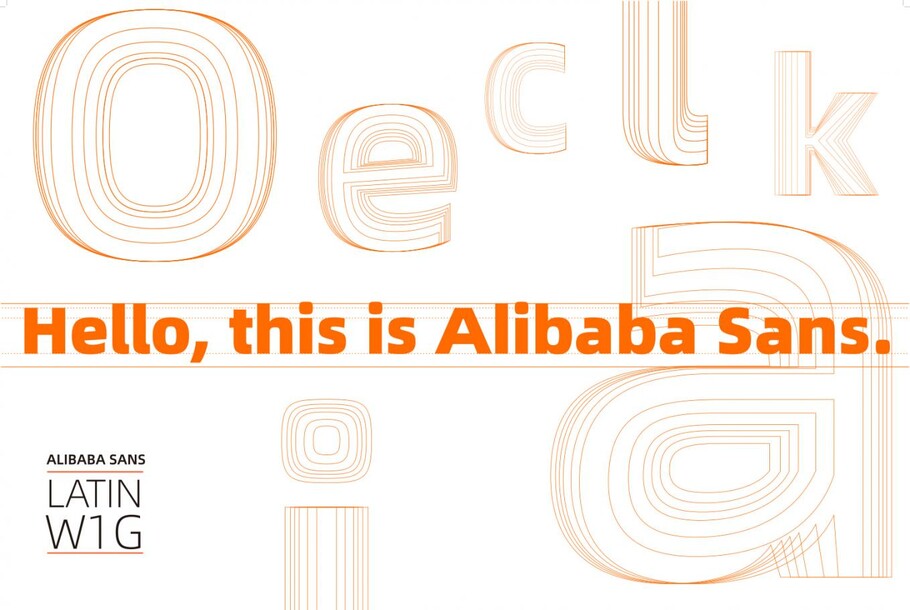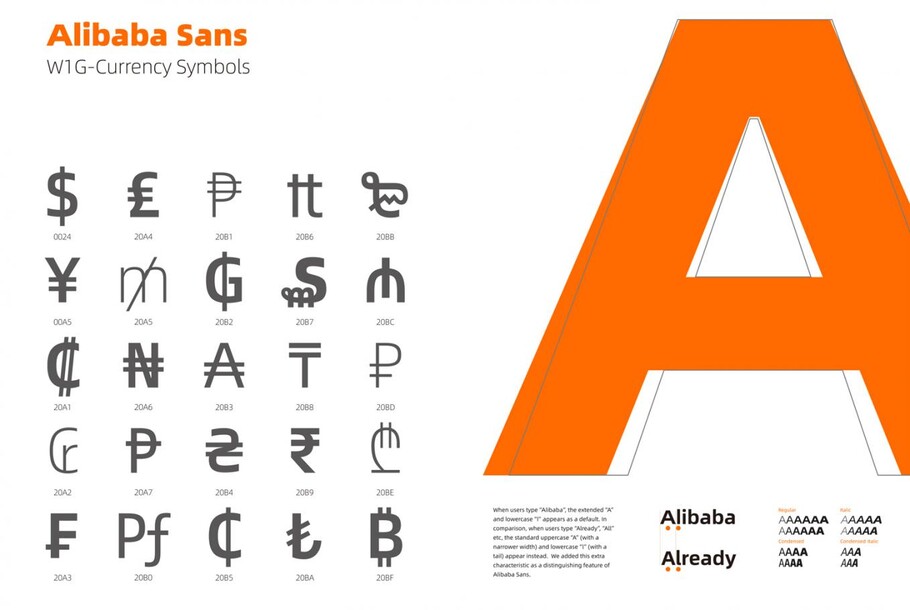
A nova fonte do Alibaba Group traz beleza e simplicidade ao ecossistema da empresa.
“ A Monotype entendeu nossos desafios únicos e entregou uma fonte que elevará nossas iniciativas de branding. ”
Alibaba Sans
Essa família de fontes personalizada, Alibaba Sans, ajudará parceiros e clientes a criar designs que estejam alinhados à marca.
O desafio
A equipe de branding corporativo do Alibaba Group enfrentou uma série de desafios de design ao utilizar diferentes fontes de código aberto em suas equipes criativas, locais de trabalho e em todo o vasto ecossistema de parceiros e fornecedores digitais.
O rápido crescimento da empresa aumentou a necessidade de uma família de tipos flexível e inovadora que permitisse aos designers experimentar com liberdade, enquanto permaneciam em conformidade com as diretrizes da marca e dos Direitos de Propriedade Intelectual e Industrial. Dada a natureza do e-commerce e do varejo como seu principal negócio, era necessário uma fonte onde os numerais e símbolos de moeda fossem de extrema importância – não apenas as letras. Para aumentar o desafio, o Alibaba Group precisava compartilhar facilmente a fonte da marca com colegas, parceiros e clientes em seu crescente mercado para criar campanhas alinhadas à marca
A solução
Aproveitando um esforço colaborativo verdadeiramente integrado, os membros da equipe de design da Monotype e do Alibaba Group iniciaram uma série de workshops intensivos focados no design e dedicados ao desenvolvimento rápido do novo conceito tipográfico que incorporaria a personalidade corporativa do Alibaba Group.
A equipe de design da Monotype, liderada pelo diretor de tipografia Akira Kobayashi, começou a abordar os desafios do Alibaba Group, desenhando primeiramente os numerais e símbolos de moeda, que eram de importância crucial para o aspecto de e-commerce do negócio. Desenhando números e letras do zero e incluindo o exclusivo “a” minúsculo, a equipe criou a Alibaba Sans. As fontes precisavam ser agradáveis aos olhos, mesmo nos pesos mais densos, e legíveis em tamanhos pequenos e grandes em qualquer dispositivo ou local – desde telas de exibição e diversos edifícios de escritório até a loja de presentes da empresa, shoppings e sites de e-commerce em toda parte
Aproveitando os resultados de uma pesquisa global com funcionários, projetada para capturar as palavras mais impactantes que os colaboradores acreditam representar o Alibaba Group, os designers refletiram a essência de ser “apaixonado”, “poderoso” e “voltado para o futuro” na Alibaba Sans. A família de fontes personalizada será lançada no festival UCAN da Alibaba Design, nos dias 27 e 28 de abril de 2019. Por meio do poder do design, as empresas agora terão um conjunto completo de fontes do sistema, o que permitirá que sejam “belas e simples.”
“ A Monotype entendeu nossos desafios únicos e entregou uma fonte que elevará nossas iniciativas de branding. Nós realmente apreciamos sua parceria como um verdadeiro especialista e extensão de nossa equipe. Gostaríamos de tornar essa nova fonte um recurso inclusivo para todos os parceiros e clientes globalmente, e de forma gratuita.” ”
Chris Tung, diretor de marketing do Alibaba Group
“ O Alibaba Group enfrentou um desafio de branding comum, mas significativo: a necessidade de transmitir os valores da marca em uma ampla gama de ambientes, tanto físicos quanto digitais. Foi um prazer trabalhar com uma equipe tão dedicada à importância da fonte e ajudar o Alibaba Group a perceber o potencial que uma fonte personalizada tem para unificar uma marca.” ”
Akira Kobayashi, diretor de tipografia da Monotype
O Diretor Criativo de Tipografia Akira Kobayashi tem quase quatro décadas de experiência e um extenso conhecimento em design de fontes japonesas, além de ser ter ganhado o 2022 TDC Medal e Keinosuke Sato Award. Após estudar na Universidade de Arte de Musashino em Tóquio por quatro anos, Akira Kobayashi aceitou seu primeiro emprego na produtora de fotocomposição Sha-Ken Co., onde esteve envolvido no longo e intrincado processo de design de fontes japonesas.
A nova fonte do Alibaba Group.